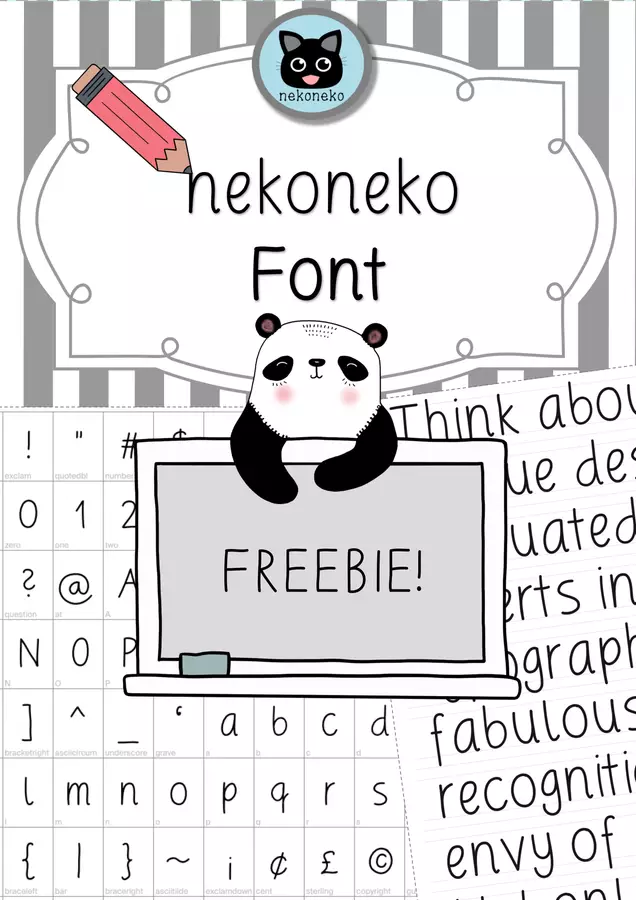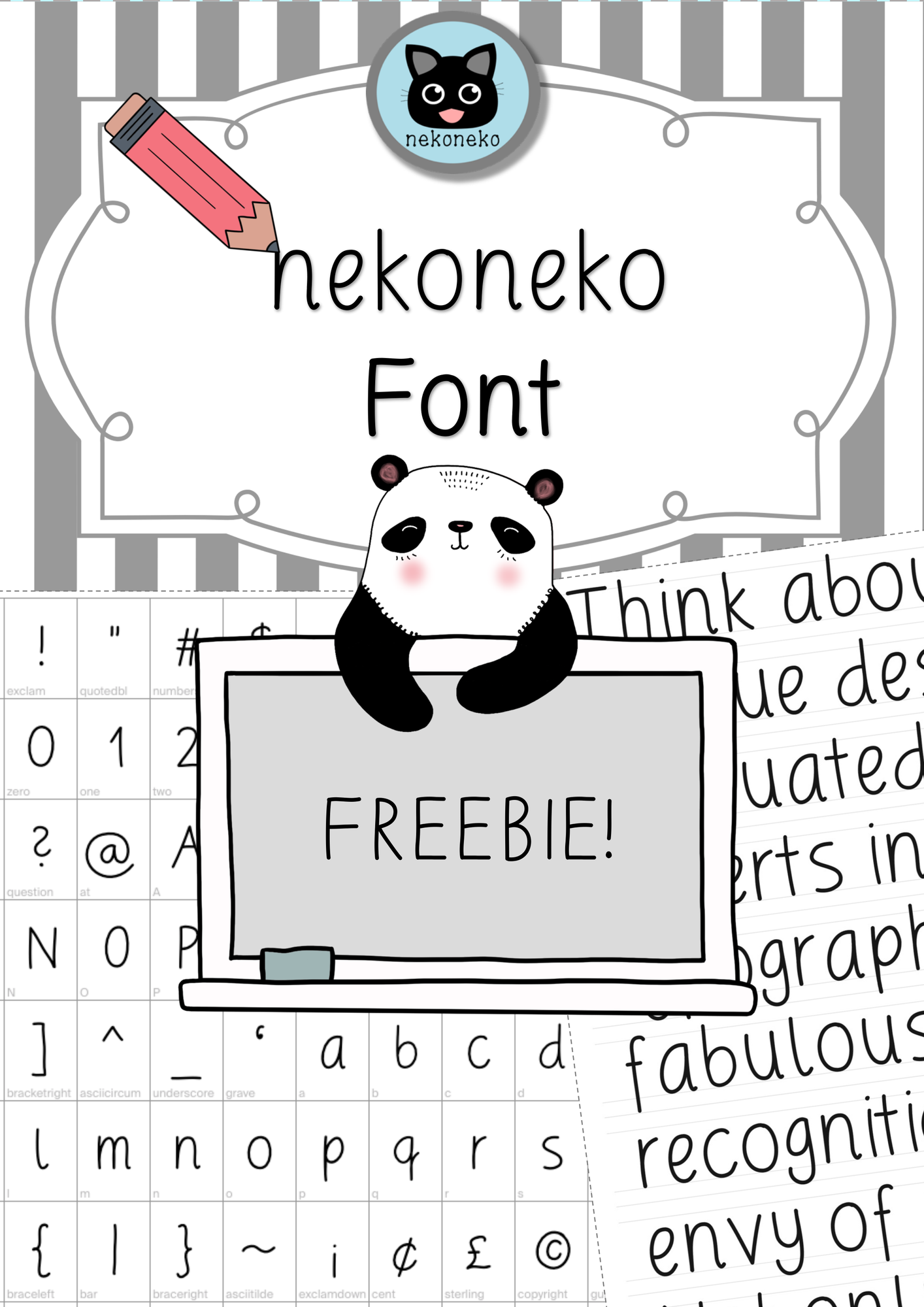
Una y otra vez, recibo encantadores cumplidos sobre mi escritura en la pizarra a partir de mis posts de Instagram sobre la palabra de la semana. Por eso ahora he editado digitalmente mis escritos para compartirlos con ustedes de forma gratuita.
nekoneko Font - ¡Mi tipografía gratis para ti!